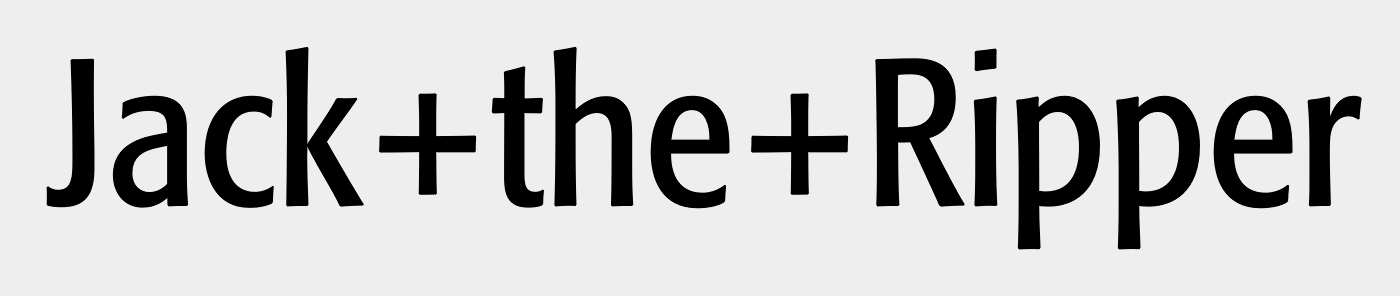
Welche Schrift für Titelseite?
die zeitgenössischen Romane beschäftigen mich immer noch. Als Brotschrift haben wir die Jenny ausgewählt, die in Einzelfällen mit der Myriad oder der Solomon kombiniert wird.
Für die Titelei sollte eigentlich ebenfalls die Jenny verwendet werden.
Jetzt würde ich aber besonders für den Schmutztitel und die Titelseite gerne eine etwas lebendigere, spannungsreichere Schrift verwenden. Sowohl die Myriad als auch die Solomon sind mir entschieden zu sachlich.
Inhaltlich handelt es sich zu einem großen Teil um esoterisch bzw. spirituell angehauchte Romane. Außerdem ist eine Krimi-Reihe geplant, für die ich mir eine eigene Schrift für die Titelseite vorstellen kann.
Leider suche ich wieder einmal viel zu unsystematisch :-( Für ein paar Anstöße wäre ich deshalb sehr dankbar :-)
Ich habe jetzt mal mit einigen Schriften getestet. Die Agilita und die Finnegan sind mir eindeutig zu steif, ebenfalls die Solomon. Die Diavlo, die ich schon mal als Brotschrift für einen Krimi eingesetzt habe, ist in größeren Schriftgraden leider nicht sonderlich lesefreundlich.
Hängengeblieben bin ich jetzt zumindest mit Blick auf die Krimireihe erst einmal bei der Amaranth. Allerdings wirkt der normale Schnitt in größeren Schriftgraden recht leicht, der fette dagegen gleich wieder zu schwer. Ein halbfetter existiert jedoch nicht.
Aber vielleicht kommen hier ja doch noch ein paar Vorschläge.
besonders für den Schmutztitel und die Titelseite
Titelseite ja, aber den Schmutztitel würde ich nicht durch eine andere Schrift aufwerten, sondern unauffällig in der Grundschrift belassen.
Mit der Formata hätte ich ein wenig Schwierigkeiten – ich kenn sie vor allem aus Sachbüchern der 90er ...
Aber vielleicht sowas in der Art?
(sorry, hatte wohl gerade einen Emigre-Schub)
Fast hatte ich mich schon für die Formata entschieden, doch dann fiel mein Blick auf die Ziffern :-(
Die Kapitel sind fast immer nur durchnumeriert. Die Zahlen einfach wie der Fließtext in der Jenny setzen möchte ich nicht, weil das zu verspielt aussieht. In der Amaranth sahen sie sehr schlicht aus, in der Formata jedoch irgendwie verzerrt, unausgewogen.
Für die Überschriften die Amaranth und für den Titel die Formata zu nehmen, behagt mir aber aus zwei Gründen nicht: Zum einen kommen dann zwei unterschiedliche Serifenlose zum Einsatz und zum anderen kann ich natürlich nicht ausschließen, dass es irgendwann auch mal einen Buchtitel mit einer Zahl geben wird.
Schön wäre also eine Schrift wie die Formata, aber mit Zahlen wie der Amaranth.
Die drei anderen Schriftvorschläge passen leider nicht, weil sie zu verspielt sind. Die Krimis tendieren doch eher in Richtung Thriller und die anderen Bücher in Richtung Esoterik/Spiritualität.
Über den Schmutztitel hatte ich mir übrigens ehrlich gesagt noch gar keine Gedanken gemacht. Vermutlich sollte ich ihn wirklich in der Brotschrift setzen.
Eine wirklich meinen Vorstellungen entsprechende Schrift habe ich bislang aber trotzdem noch nicht gefunden. Die meisten haben ähnliche Ziffern wie die Formata, aber genau von diesen will ich eben weg. Bei den Bree-ähnlichen hat die 1 häufig einen breiten Fuß, der nicht in das Gesamtdesign passt oder die Buchstaben sehen für Krimis zu weich aus.
Wir haben jetzt aber sowieso beschlossen, uns für das Redesign Zeit bis zum Jahresende zu nehmen, so dass ich in Ruhe weiter experimentieren kann.
Gern. Die Empfehlungen bei Identifont sind ja auch nicht immer vollständig und treffend – aber für einen ersten Anlauf kann es schon oft sehr nützlich sein.
Auch wenn ich nicht weiß, auf welche Schriften Du nun inzwischen schon gestoßen bist, hier noch ein paar Anregungen, welche Serifenlose noch zur Jenny passen könnten:
Richtung Formata:
Je mehr Schriften ich probiere, desto mehr gelange ich zu der Erkenntnis, dass ich mich doch für die Formata entscheiden sollte. Ihr Charakter passt zu Krimis und sie harmoniert gut mit der Jenny. Dass mir die 2 nicht gefällt - okay, diese Kröte muss ich schlucken. Und so schlimm finde ich sie inzwischen auch nicht mehr.
So wie es aussieht, wird es also wohl nun doch die Formata werden.